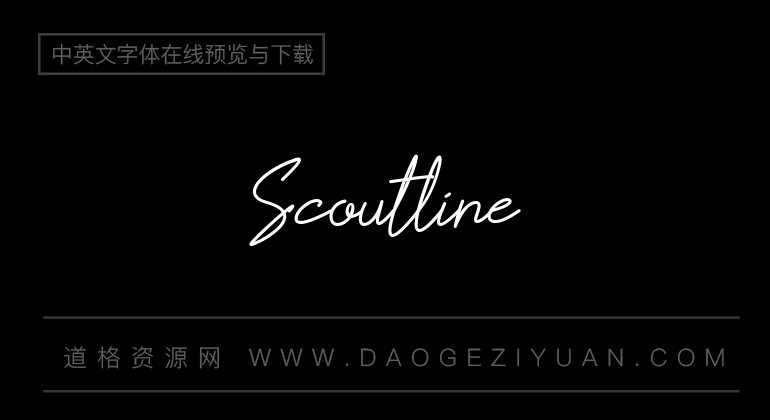
Scoutline
Scoutline 字体是一种具有复古风格的手写字体,由荷兰设计师 David Kerkhoff 设计,由 Fonts.com 提供。Scoutline 字体具有细腻的笔画,清晰的线条,给人以古典、精致、优雅的感觉。它拥有丰富的字形,包括大小写字母、数字、标点符号和多种特殊符号。Scoutline 字体可用于设计海报、书籍封面、网站标题、名片等,为设计师提供了丰富的创意空间。
Scoutline是一款非常不错的手写艺术字体,具有很好的视觉感,适合于文化类的宣传设计、商业类品牌的广告和产品包装设计以及个性化文字排版等较多场景。
Scoutline字符映射图